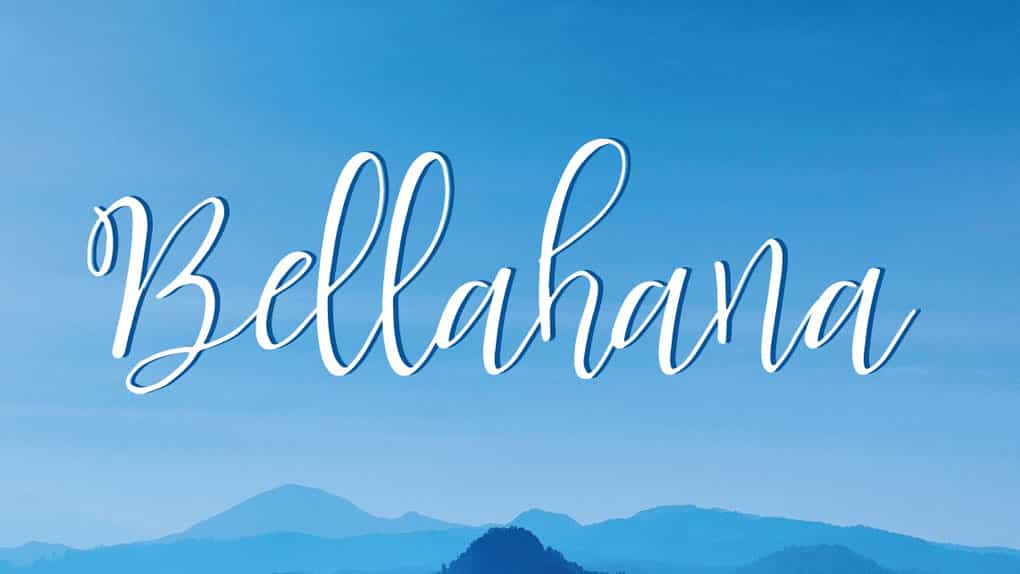
فونت انگلیسی Bellahana Script Font
فونت انگلیسی Bellahana : مجموعه Bellahana یک فونت دست نویس است. این فونت برای دعوت نامه عروسی یا وبلاگ شما مناسب است. میتوانید یک لوگو ایجاد کنید یا فقط برای تجارت کوچک خود، جلد کتاب، لوازم‌التحریر و موارد دیگر استفاده کنید.